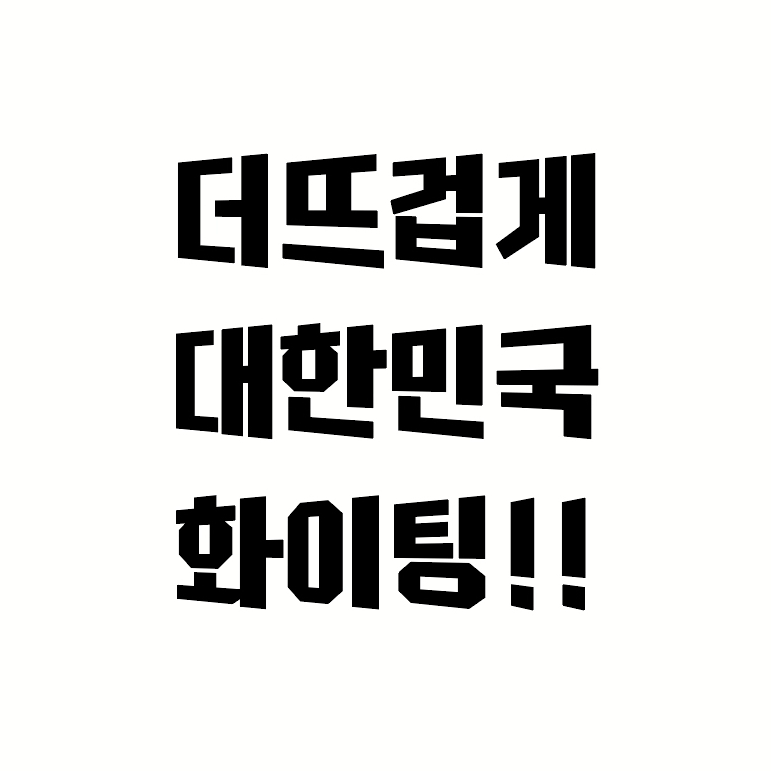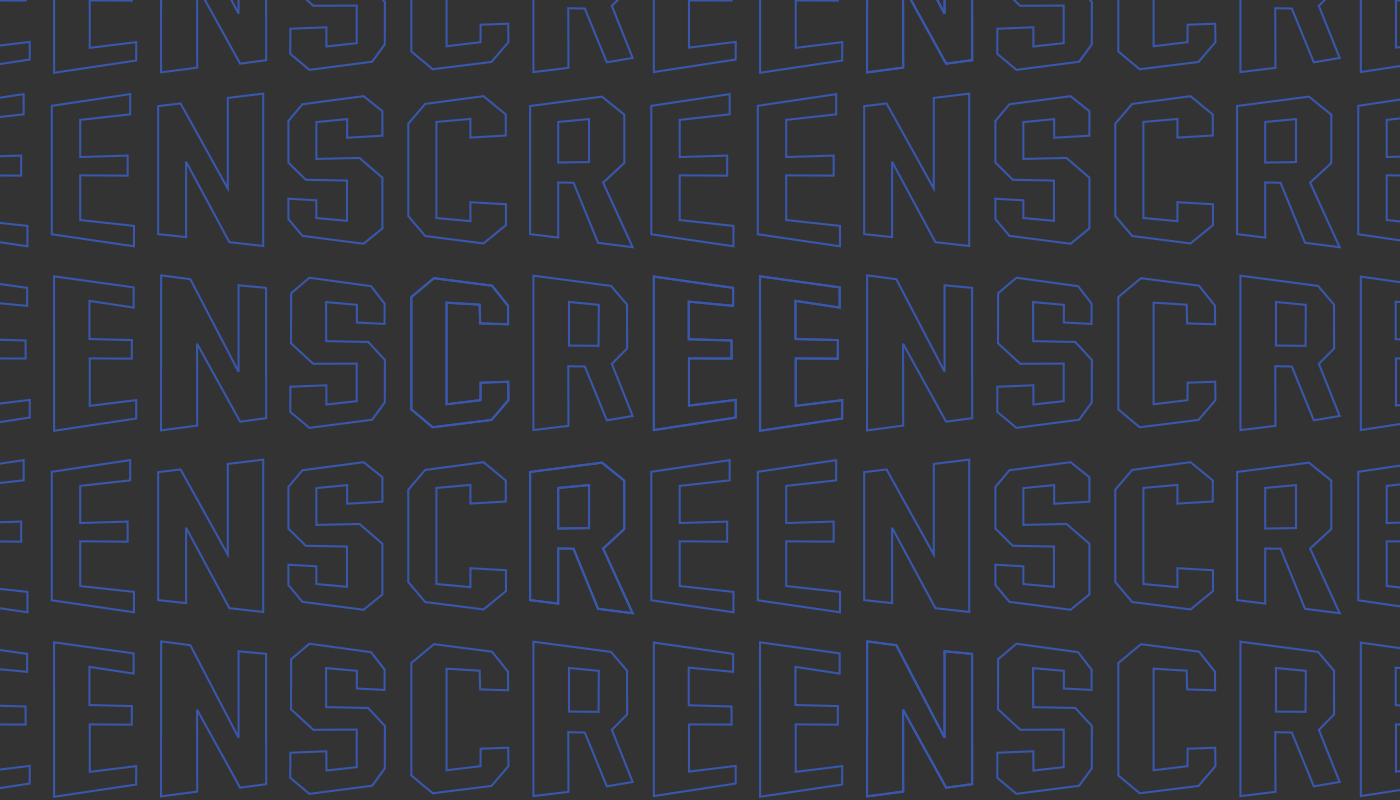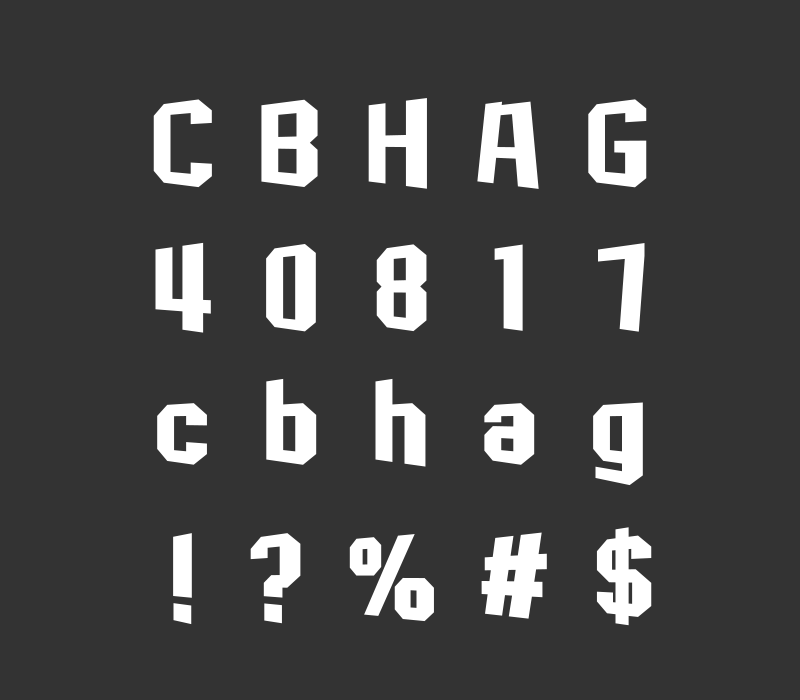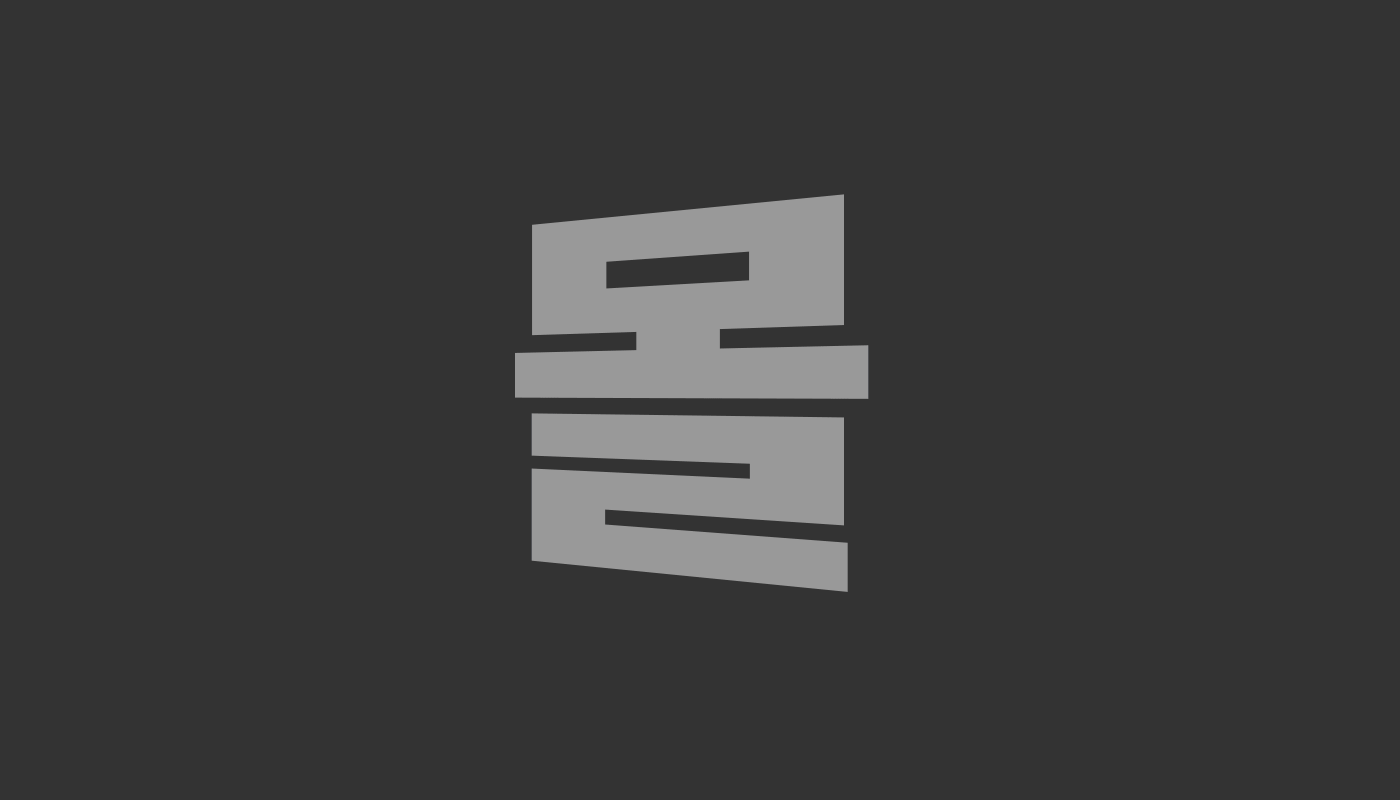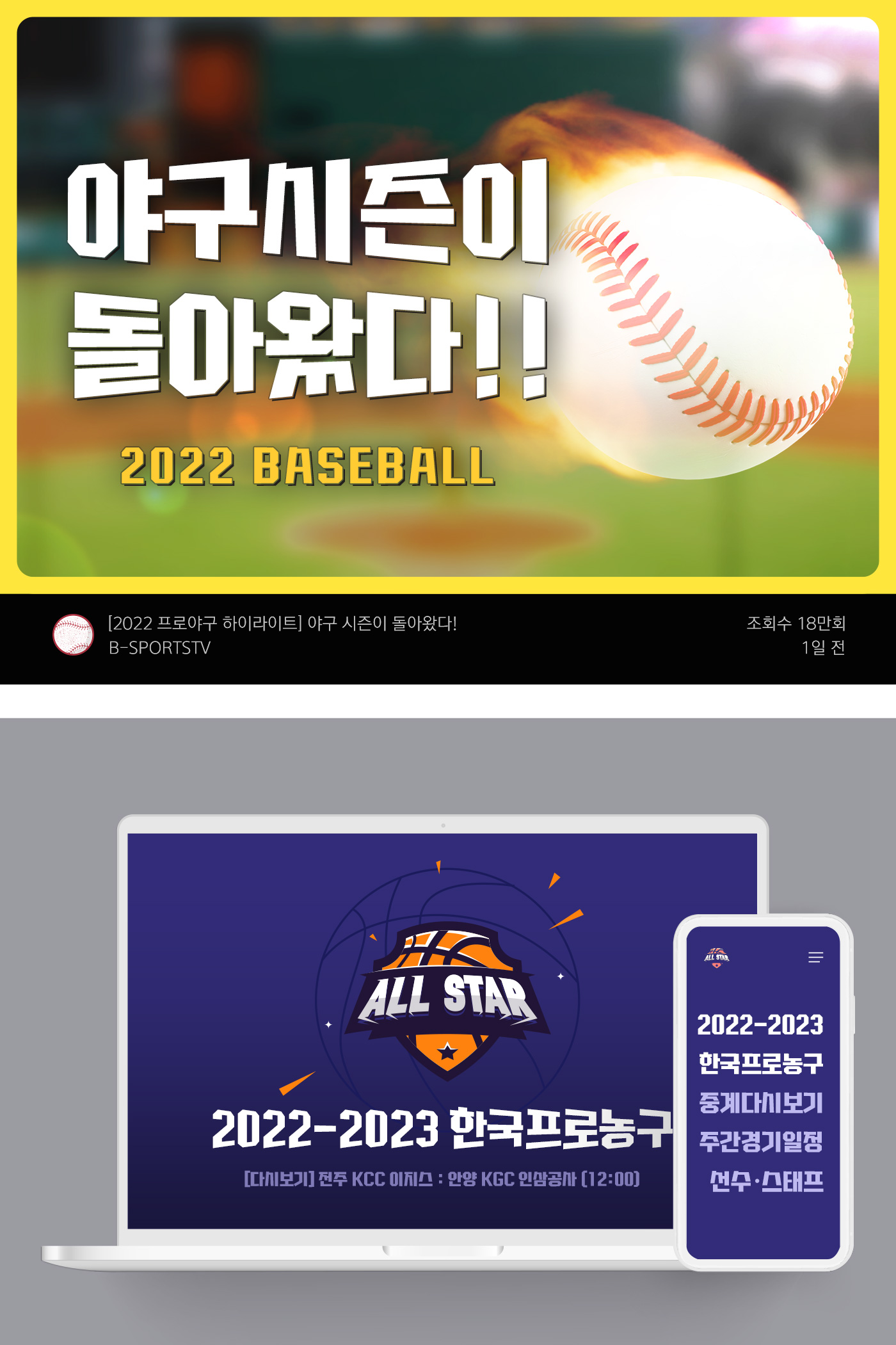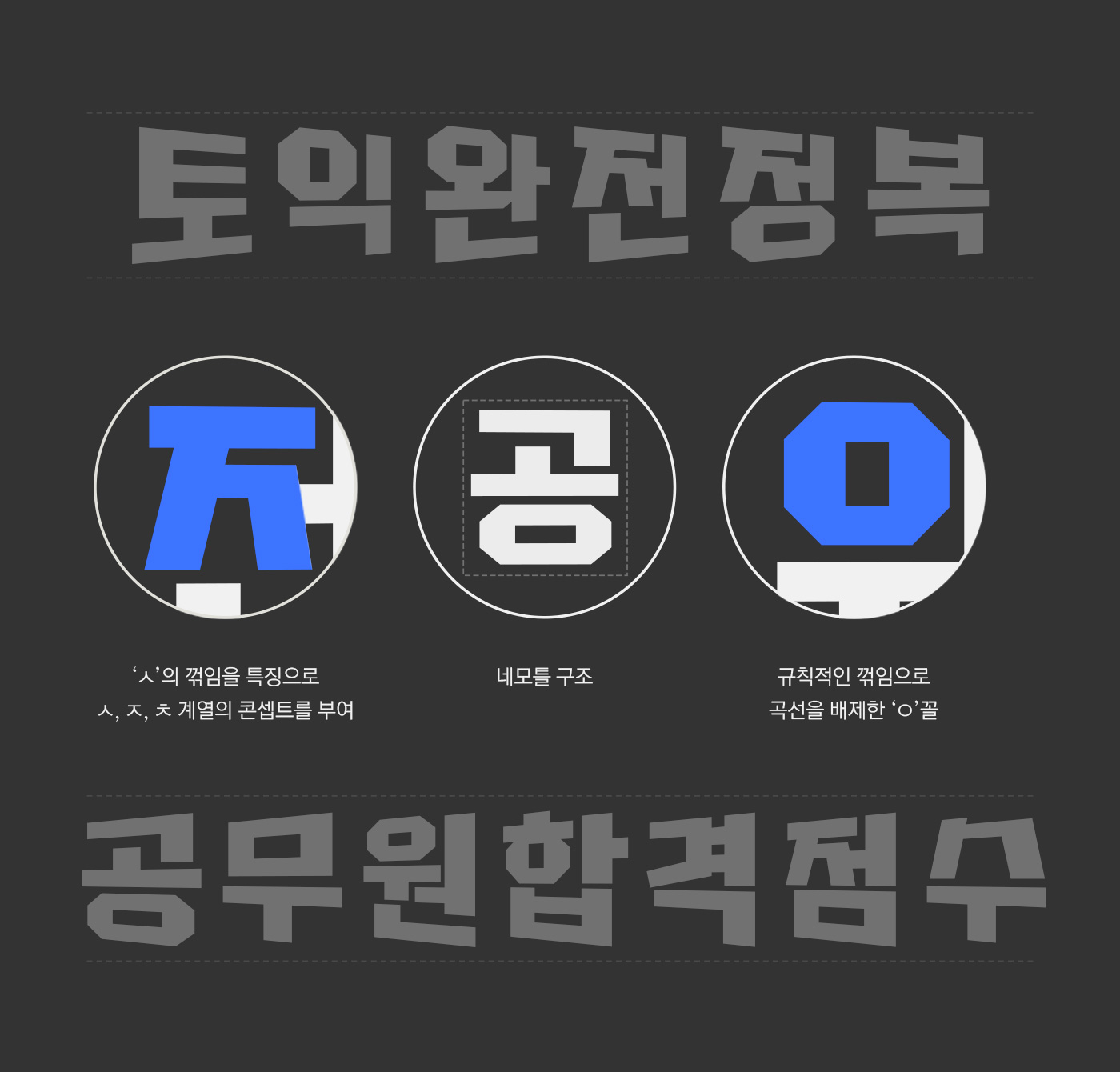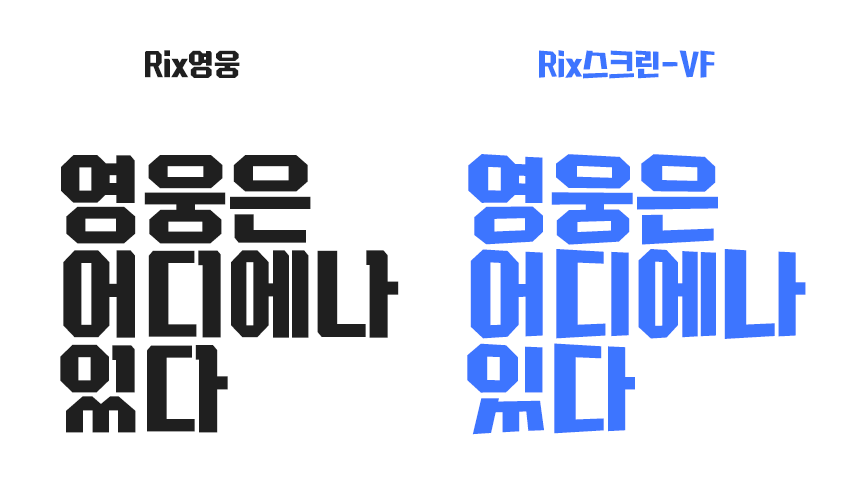
일상의 발견! 좌우로 배리어블, Rix스크린-VF
안녕하세요. 오늘은 11월의 신서체「Rix스크린-VF」를 소개합니다. Rak배리어블, 도로롱배리어블 UpDown/ZigZag, 블랙산스배리어블 Wiggle에 이어 벌써 RixFont의 4번째 배리어블 서체입니다! 이번에는 슈퍼 히어로처럼 강하고 각진 형태가 특징인 Rix영웅 폰트에서 변형을 준 서체인데요. Rix스크린배리어블의 제작을 맡으신 최법호 디자이너와의 인터뷰 준비했습니다 :)
안녕하세요. 소개 한번 부탁드립니다.
안녕하세요. 이번 11월 신서체 Rix스크린-VF로 처음 인사드리게 된 폰트 디자이너 최법호입니다.
어떻게 기획&제작을 맡으셨는지 궁금해요.
지하철을 기다리다 옆에 스크린도어 광고를 보게 되었습니다. 측면에서 보니 광고에 있는 글자들이 기울어져 보이는데, 문득 ‘글자마다 기울기가 있으면 재밌겠다’의 단순한 발상으로 기획하게 되었습니다.
그래서 폰트명이 스크린이군요! 가장 신경 쓴 디자인 포인트가 있다면?
먼저 글자를 입체적으로 잘 표현하기 위해 어떤 폰트가 잘 어울릴까 고민을 많이 했습니다. Rix영웅의 특징인 꽉 찬 네모꼴과 직선적인 획의 꺾임이 입체적으로 잘 표현될 것 같아 베이스를 두고 몇몇 자소들을 수정하였습니다. 그리고 베리어블을 활용하여 좌, 우 어디서든 보는 재미있는 효과를 주어 폰트 활용성을 높였습니다. 또한, 사용자가 수치 조절을 통해 원하는 만큼의 정도를 설정할 수 있습니다.
이 폰트를 누구에게 추천하나요?
처음 기획했을 때는 큰 광고 포스터에 쓰이면 괜찮겠다 생각했습니다. 하지만, 예능 자막이나 유튜브, SNS 썸네일 등 다양하게 사용해도 잘 어울릴 것 같습니다.
처음 폰트를 맡아 제작하신 소감?
첫 폰트부터 베리어블로 제작을 하는 거라 배워야 할 게 정말 많았는데, 박용락 프로님과 저희 폰트 디자인팀 팀원들이 도와주셔서 많이 배울 수 있었습니다. 앞으로 재밌고 다양한 폰트로 찾아올 테니 기대 많이 해주세요!
생활 속에서 발견하다
Rix스크린-VF의 시작은  지하철의 스크린도어 광고였습니다. 쉽게 지나칠 수 있는 일상의 한 부분이 발상의 전환이 되고, 새로운 배리어블 서체로 탄생했습니다.
*배리어블 폰트란?
축을 통해 사용자가 직접 글자의 속성을 조절하여 하나의 서체로 다양한 형태를 구현할 수 있는 폰트
Rix스크린-VF의 원도인 Rix영웅 서체와 어떻게 다른지 한번 볼까요? 두꺼운 굵기와 듬직한 형태, 네모꼴의 속공간은 동일하지만 영웅체는 각진 세리프에 꺾임이 있는 획이 특징이었는데요. Rix스크린-VF에서는 일부 획과 자소의 형태가 변경되었습니다.
세리프 없이 깔끔해진 세로 획, 꺾임이 더 느껴지도록 변형된 ㄱ과 ㅅ, ㅈ, ㅊ 자소에 독특한 꺾임을 주어 레트로적인 이미지와 속도감이 더욱 느껴지는 컨셉을 부여하여 최근 동향의 콘텐츠에 더욱 어울리는 느낌으로 리디자인되었습니다.
좌우로 움직이는 배리어블
배리어블 축을 이동했을 때 좌우로 글자 폭이 달라지며 기울어지는 각도로 원근감이 느껴지도록 설계했습니다. 서체는 기본적으로 단단하고 두꺼운 획으로 기울기가 있어도 안정감이 느껴집니다.
영문, 숫자 및 약물에도 적용되는 배리어블 기능으로 국문과 자연스럽게 혼용하여 쓸 수 있습니다. 역동적인 움직임과 깔끔한 디자인으로 주목도가 필요한 다양한 콘텐츠에 쓰기 좋아요.
| 이렇게 활용해 보세요
힘 있는 형태와 강렬한 좌우 기울기를 가진 Rix스크린-VF는 주목성이 필요한 광고, 배너, 썸네일 등 디자인에 활용하기 좋습니다. 역동적인 폰트의 인상 덕분에 스포츠 관련 콘텐츠에 특히 잘 어울리는 것 같아요!